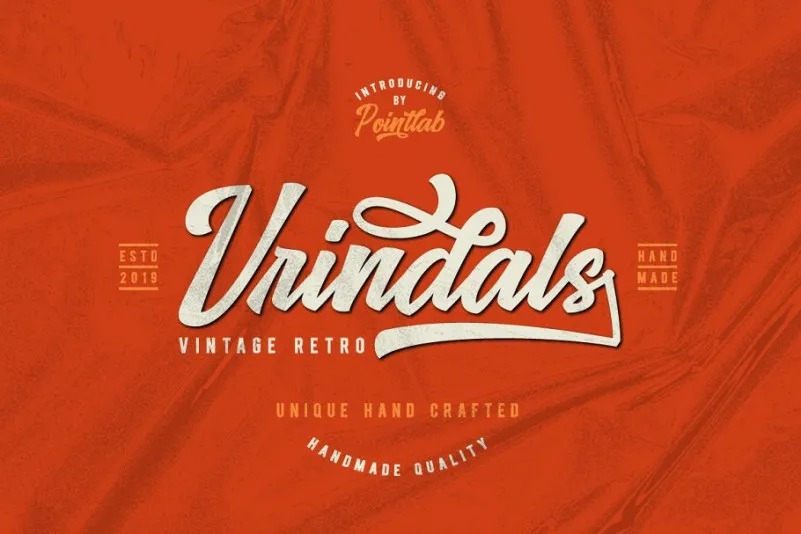
Vrindals Script Font
Vrindals Script é uma tipografia script contemporânea que combina a sofisticação do estilo retro com os contrastes modernos das serifas geométricas. Este tipo de fonte carrega consigo um ar vintage enquanto ainda mantém seu caráter moderno, criando uma vibe única perfeita para projetos em que se deseja incorporar elementos antigos e atemporais. Inspirado nos estilos retro e na letra artesanal, a M.0Type adicionou sua própria personalidade a cada curva, dando ao tipo um toque único e distintivo. A Vrindals Script é especialmente indicada para uso em logotipos, frases escritas à mão, embalagens de produto, cabeçalhos, cartazes, materiais de merchandising, mídia social e cartões de convite. Ela vem acompanhada de uma fonte complementar leve de marcadores que se combinam perfeitamente com a Vrindals Script. Adicionalmente, a fonte oferece um conjunto de Swash muito útil para tornar seus trabalhos ainda mais personalizados e interessantes. A Vrindals Script é uma fonte script moderna e versátil, perfeita tanto para estilos tradicionais quanto para os mais contemporâneos. Sua bacia leve proporciona um equilíbrio excelente com a fonte complementar, tornando-a perfeitamente adequada para diversos projetos gráficos.